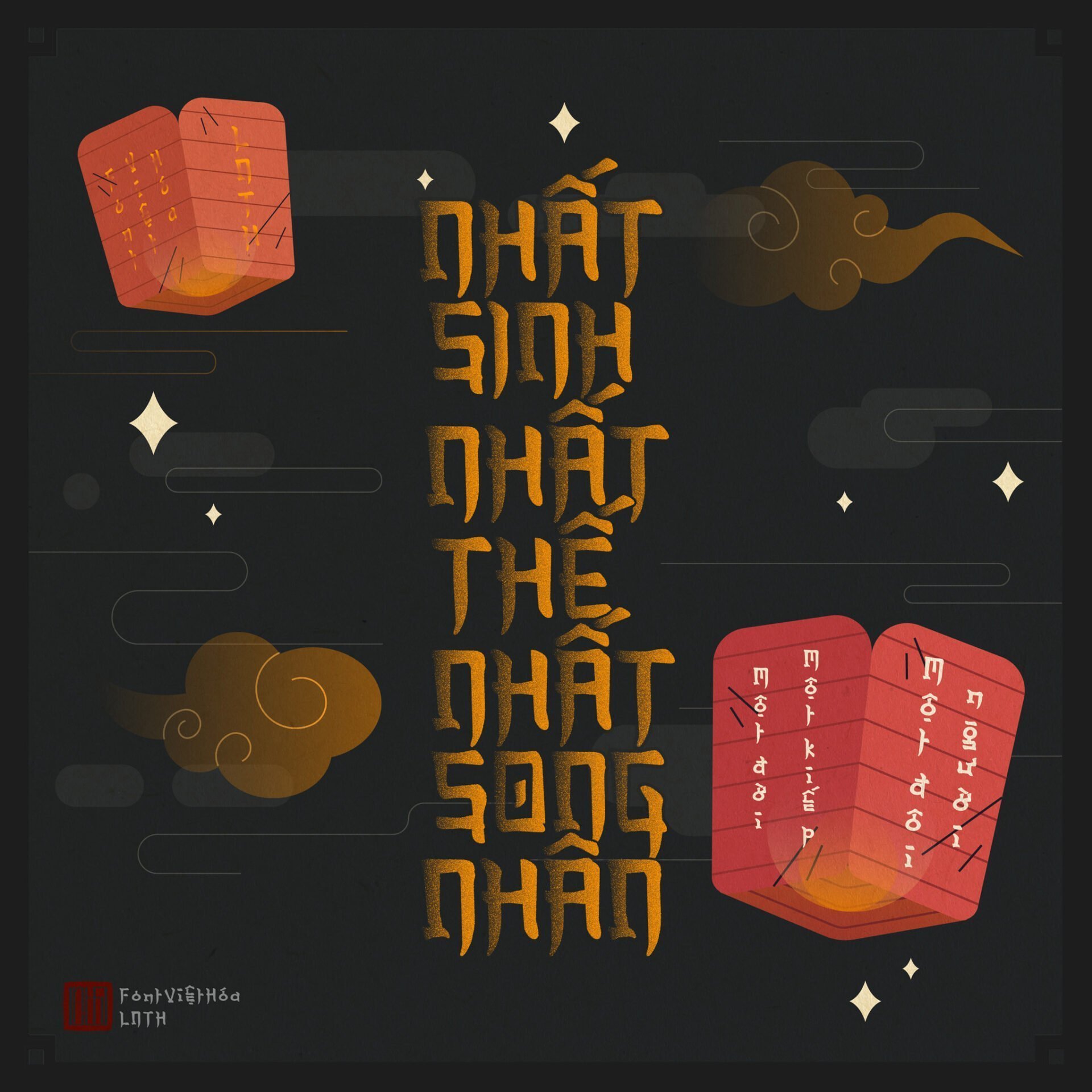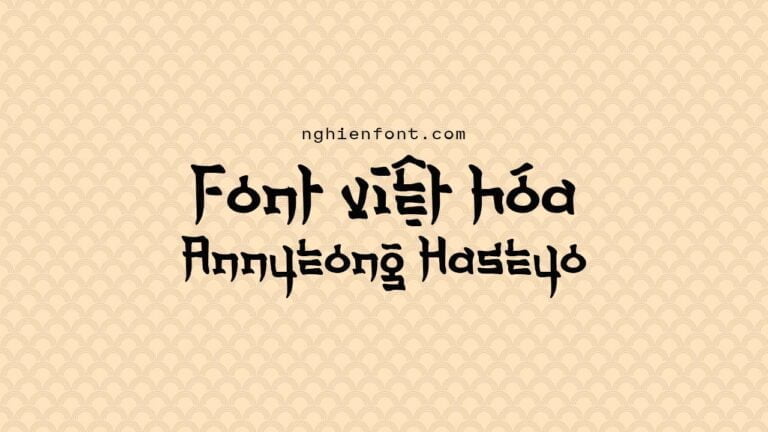
LNTH A Annyeong Haseyo là một kiểu font việt hóa đẹp mắt, các nét chữ của font được lấy cảm hứng từ các ký tự của Hàn Quốc mang đến một vẻ đẹp của chữ thư pháp.
Font phù hợp cho các thiết kế kiểu thư pháp thư bìa truyện, poster, thiệp, trang trí hoặc bất kỳ thiết kế nào khác cần 1 kiểu chữ hiển thị ấn tượng và đẹp mắt.
Font việt hóa LNTH A Annyeong Haseyo Preview